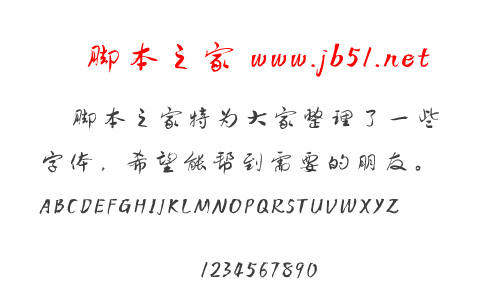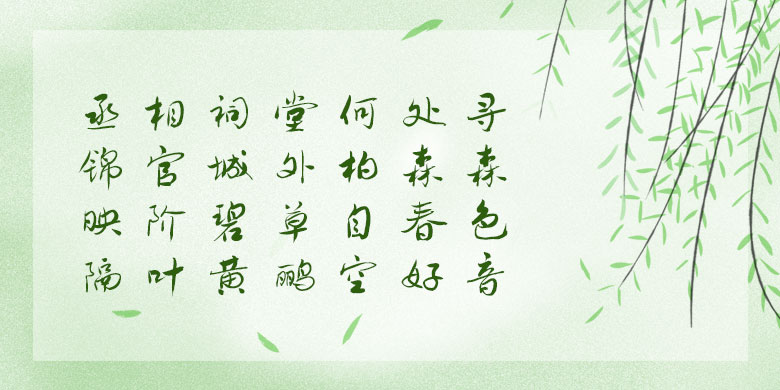
方正字跡-賀飛行草字體是作者賀飛繼行楷之后的又一款“美書”字體。為了實(shí)現(xiàn)字體在更多的領(lǐng)域中得以應(yīng)用的愿景,給人以更強(qiáng)的視覺沖擊力,所以,作者取“行書之法”,顯“草書之意”,使之“八面出鋒”,靈動(dòng)與美妙得以詮釋!歡迎喜歡方正字跡-賀飛行草字體的朋友前來下載使用。